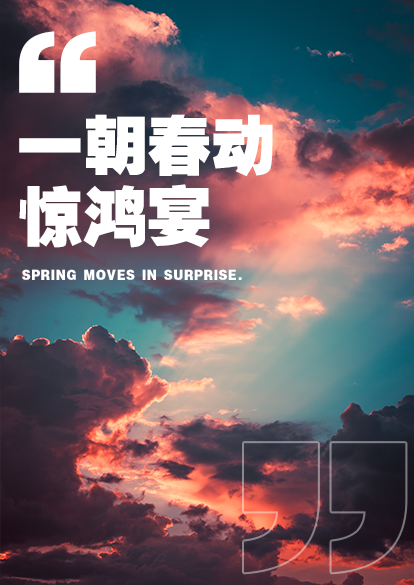
励字超黑简繁
Dream-ChaoHeiGBT
字体名称:
励字超黑简繁
字符集:
GBT
字体语言:
简繁
书体类型:
黑体
字体类型:
普通字体
字体字重:
常规(Regular)
笔画超粗而有力,字形结构严谨,朴素大方,稳重醒目,特点是没有衬线装饰,字面呈正方形的超粗壮字体,笔划超粗壮有力,撇捺等笔画不尖,字形端庄。